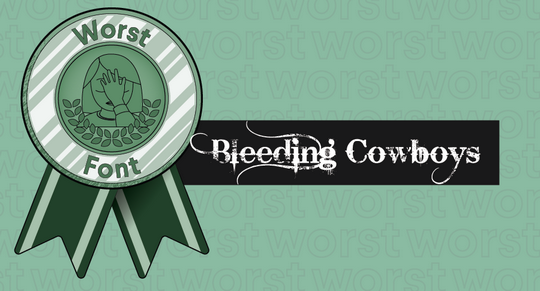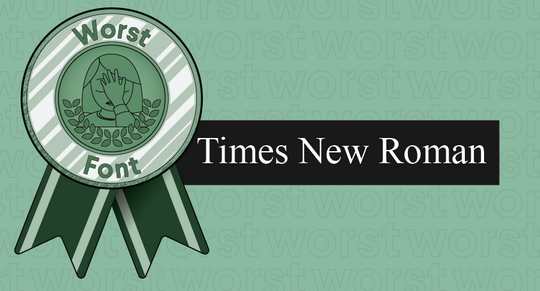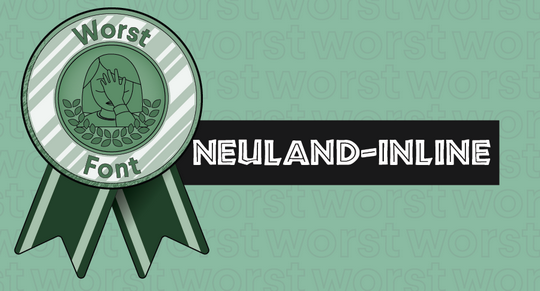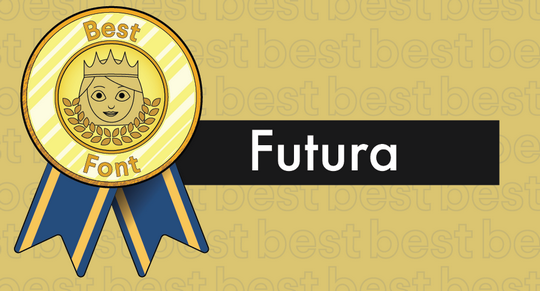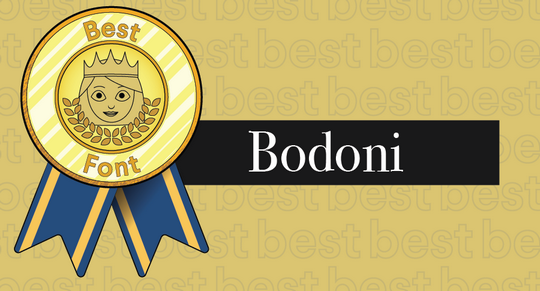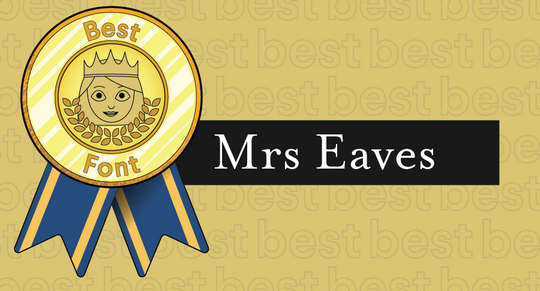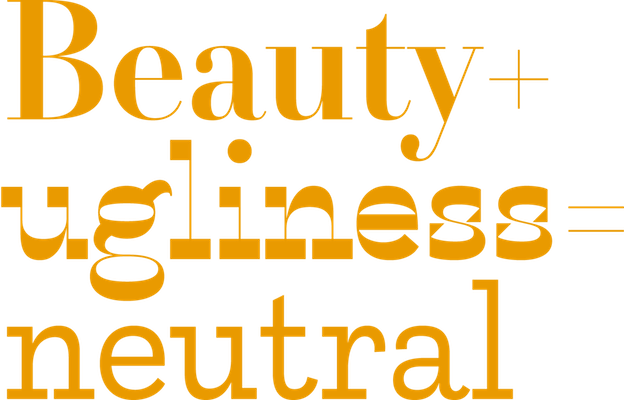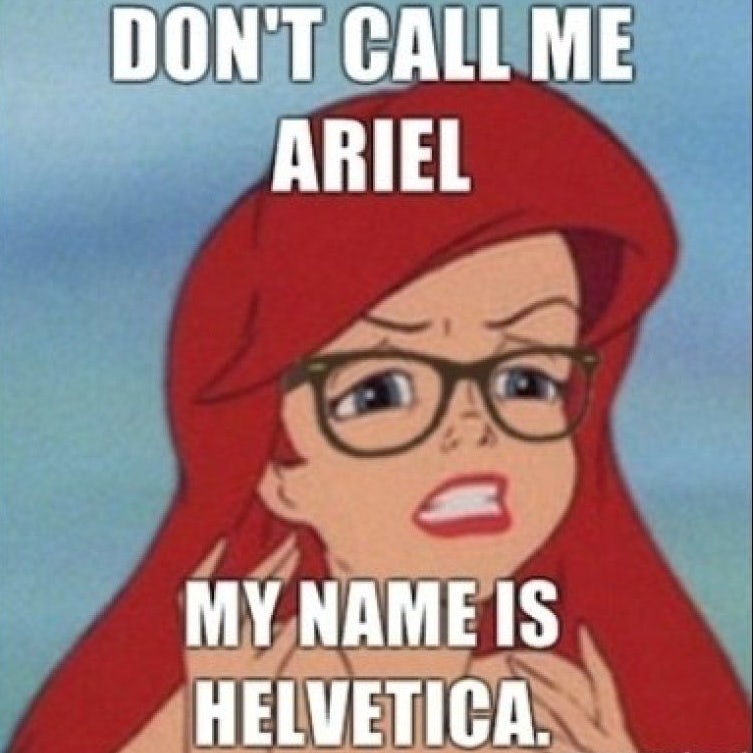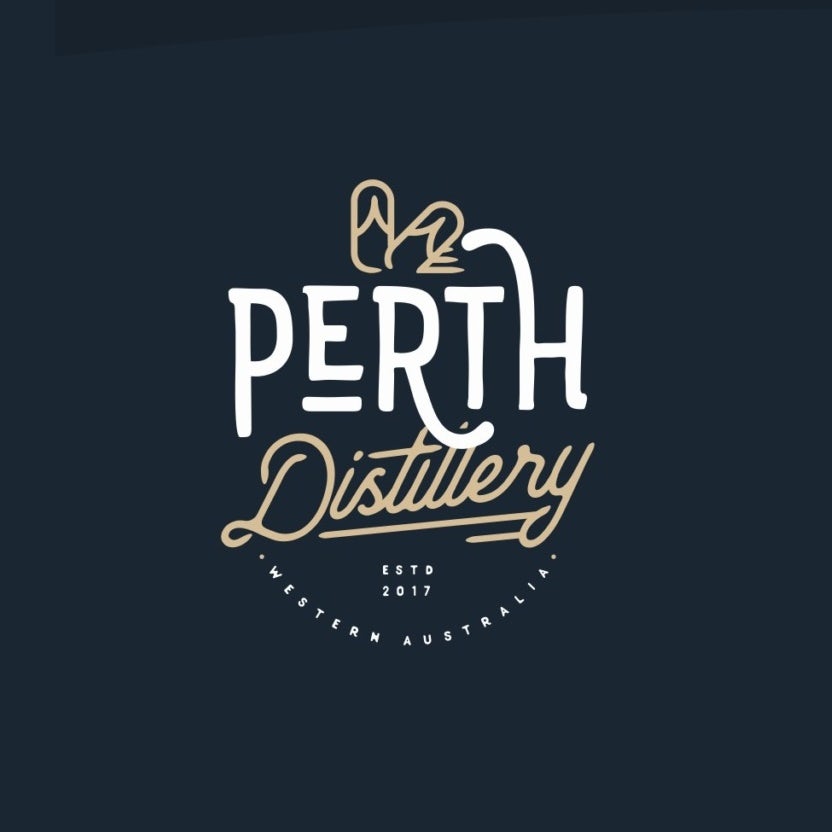
Шрифты – это наборы графических символов, используемых для представления письменного текста. Они включают в себя все символы алфавита, цифры, знаки препинания, специальные символы и другие графические элементы, которые позволяют создавать текстовую информацию в печатной или цифровой форме.
Шрифты используются в различных сферах, включая печатное издательство, веб-дизайн, графический дизайн, рекламу, упаковку, мобильные приложения и многое другое. Они играют важную роль в создании визуального образа текста и могут повлиять на восприятие контента аудиторией.
К счастью, в наши дни вы больше не ограничены шрифтами, предварительно загруженными в Microsoft Word. Тысячи хороших шрифтов доступны для скачивания в Интернете, а мир талантливых дизайнеров создает уникальные шрифты, такие же, как бренды, которые их используют. Не каждый шрифт хороший. На самом деле, есть тонна плохих шрифтов, скучных, неразборчивых и просто безобразных. Это не только наше мнение: есть научные причины, по которым некоторые шрифты выглядят красиво, а другие заставляют нас съеживаться.
Чтобы помочь вам найти идеальный шрифт для вашего проекта, мы рассмотрим лучшие и худшие шрифты, а также то, что делает их эффективными (или нет).
Некоторые из лучших шрифтов.
Что делает хороший шрифт?
Даже если они могут сильно отличаться друг от друга, у лучших шрифтов много общего. Это включает:
• Даже кернинг.
• Консистенция.
• Баланс.
• Разборчивость.
Кернинг.
Кернинг – это пространство между двумя символами. Слишком мало места, и шрифт не читается, потому что буквы смешиваются вместе. Слишком много места, и трудно сказать, предназначено ли это место для разделения букв или слов. Неравномерное количество места от буквы к букве? Это выглядит просто неловко и безобразно.
Futura и Helvetica – два примера шрифтов, которые очень легко читаются благодаря их равномерному кернингу – независимо от того, являются ли буквы жирными или тонкими, их расположение дает читателю ощущение чистого пробела.
Иллюстрированная награда за лучшие шрифты в сочетании с гарнитурой Futura
Futura – это чистый шрифт с равномерным кернингом
Консистенция.
Согласованность означает, что все буквы, цифры и любые другие используемые символы сохраняют одинаковый внешний вид. Если буква «A» шрифта имеет засечки, мы ожидаем, что у буквы B тоже будут засечки, и так далее.
Точно так же, если шрифт имеет толстые буквы с мягкими закругленными углами, но этот стиль не распространяется на его цифры или знаки препинания, шрифт кажется непоследовательным и даже неполным.
Иллюстрированная награда за лучшие шрифты в сочетании с гарнитурой Mrs Eaves
Mrs Eaves имеет равномерное распределение твердых краев по закругленным углам
Сбалансированные шрифты.
Сбалансированное сочетание толстого и тонкого, тяжелого и легкого, является важной составляющей хорошего шрифта.
Didot – превосходный шрифт, который использует драматические различия между толстыми и тонкими штрихами, при этом сохраняя равновесие. Bodoni – другой известный пример хорошо сбалансированного шрифта с его сильными, твердыми вертикальными штрихами и более легкими арками и изгибами. Его засечки добавляют немного стильного стиля, который также напоминает противовесы, держащие буквы в вертикальном положении.
Иллюстрированная награда за лучшие шрифты в сочетании с гарнитурой Bodoni
Bodoni имеет равномерное распределение веса, как классный шрифт
Разборчивые шрифты.
И, наконец, шрифт должен быть разборчивым. Шрифт, который вы не можете прочитать, похож на изображение, которое настолько занято, что вы не можете сказать, каким оно должно быть. Проверьте, является ли шрифт разборчивым, написав в нем различные слова, убедившись, что вы используете каждую букву и несколько разных буквенных комбинаций. Увеличьте его, затем уменьшите, чтобы увидеть, есть ли такой размер, при котором его становится трудно читать. Если вам нужен такой маленький текст, выберите шрифт с таким размером.
Иллюстрированная награда за лучшие шрифты в сочетании с гарнитурой Garamond
Garamond является классическим шрифтом, потому что он элегантен и разборчив в разных размерах.
Шрифты, которые выдержали испытание временем, как и Garamond, остаются популярными среди дизайнеров, потому что они разборчивы в различных размерах, цветах и ​​композициях. Sans Serifs особенно хороши для поддержания разборчивости независимо от контекста: отсюда и стойкость таких шрифтов, как Helvetica .
Некоторые из худших шрифтов.
Что делает шрифт плохим?
Есть много способов, которыми шрифт может быть плохим. Многие популярные шрифты были чрезмерно истощены. Шрифты, которые не сочетаются с нашим внутренним пониманием баланса, также выглядят ужасно. Еще больше шрифтов не работает, потому что их слишком много, чтобы их можно было прочитать, в то время как у других есть противоположная проблема: в них нет ничего уникального, поэтому они не выделяются. А еще есть шрифты, которые пытаются выглядеть экзотично, но при этом чувствовать себя так же аутентично, как и меню Taco Bell. Давайте разберемся, как худшие шрифты выглядят подробно.
Чрезмерно используемые шрифты.
Некоторые шрифты настолько перегружены, что стали универсальными. Некоторые известные примеры включаютCopperplate Gothic, Brush Script and Souvenir . Brush Script была чрезвычайно популярна с 1940-х по 1960-е годы до такой степени, что сегодня она все еще ощущается устаревшей и чрезмерно используемой. Точно так же «Сувенир» постоянно закрепляется в наших умах как «шрифт 70-х годов».
Иллюстрированная награда за худшие шрифты в сочетании с гарнитурой Trajan Pro
Trajan Pro использовался на многих постерах фильмов и обложках книг, что он потерял свою привлекательность.
Другие часто используемые ретро-шрифты, от которых вам следует держаться подальше? FF Blur and Trajan Pro. Это не значит, что они плохие шрифты как таковые. Они были сделаны так много раз, что теряют всякую привлекательность.
Несбалансированные шрифты.
Когда шрифт сбалансирован, мы читаем его как эстетически приятный.
красивые и некрасивые варианты шрифта шрифта Karloff желтого цвета
Когда мы видим дисбаланс, мы видим уродство, и когда шрифт полностью нейтрален, он читается как где-то посередине. через Питера Билака
Все это означает, что вес шрифта – расположение его более толстых линий – распределяется таким образом, что он не опрокинулся бы, если бы это был материальный объект.
Возьмите три варианта изображенного здесь Карлоффа: светильник типографии шрифта Питера Билака, разработанный для проверки его гипотезы о том, что распределение веса шрифта определяет, будет ли он уродливым или красивым. Худшие шрифты несбалансированы, что делает их уродливыми.
Нечитаемые шрифты.
Некоторые из худших шрифтов, такие как Jokerman , почти не нравятся , потому что они несут тонну бесполезного смысла, который отвлекает зрителей от текста, который они пытаются прочитать.
Другой известный непопулярный, уродливый шрифт, Bleeding Cowboys, не нравится дизайнерам из-за того, насколько он занят и непредсказуем. Случайное угасание букв? Откуда взялась эта линия и куда она пойдет?
Иллюстрированная награда за худшие шрифты в сочетании с гарнитурой Bleeding Cowboys
Ковбои кровоточат, как и наши глаза.
Скучные шрифты.
И еще есть шрифты, которые просто скучны, что делает их плохим выбором шрифта. В этих шрифтах нет ничего удивительного, потому что в них нет ничего выдающегося, точка.
Arial – один из примеров шрифта, который мы все видели миллион раз раньше. Он выполняет свою работу, но это все. Это ничего не добавляет к дизайну, оно не передает бренд осмысленно.
Хотя бывают случаи, когда неуместный шрифт – это именно то, что вам нужно, существует множество хороших шрифтов, которые могут придать индивидуальность при переходе на задний план (см. Ниже раздел «Лучшие шрифты»). Обычный шрифт, такой как Times New Roman , настолько ничем не примечательн, что на самом деле может отвлечь внимание.
Иллюстрированная награда за худшие шрифты в сочетании с гарнитурой Times New Roman
Times New Roman распространена не только потому, что она отходит на задний план – она ​​вообще лишена индивидуальности
Fauxotic ™ шрифты.
Некоторые из худших шрифтов восполняют отсутствие индивидуальности с подражанием. Comic Sans , например, не в состоянии собрать супергероя из комиксов, написанных от руки. И если вы не пишете сценарий фильма, Courier  никого не обманет тем, что ваш опус был написан на старинной пишущей машинке.
Некоторые шрифты выглядят экзотично, имитируя элементы дизайна, связанные с конкретными культурами. Papyrus и Neuland-Inline являются одними из самых известных преступников. А  Bonzai’s letters имитируют мазки кисти, используемые в китайской каллиграфии, ручной характер которых теряется на статическом шрифте. Основная проблема с этими шрифтами заключается в том, что они выглядят одинаково и в лучшем случае выглядят дешевыми, а в худшем – культурно нечувствительными.
Иллюстрированная награда за худшие шрифты в сочетании с гарнитурой Neuland-Inline
Шрифты, которые соответствуют другим культурам, чувствуют себя отвратительными и нечувствительными в 21-м веке
Выбор лучшего шрифта для вашего дизайна.
Хотя плохие шрифты – это повсеместно плохой выбор, хороший шрифт автоматически не является хорошим выбором для вашего проекта. Правильный шрифт для вашего дизайн-проекта должен состоять из двух вещей:
• Хорошо продуманный и эстетичный
• Подходит для вашего бренда
круглый логотип с геометрическими линиями, показывающими ромбовидную форму рядом с геометрическим шрифтом
Этот шрифт продолжает геометрический облик, созданный логотипом этой компании, создавая современную, ориентированную на точность индивидуальность бренда.
В дизайне Arthean для Planet Diamonds мы видим прекрасный пример шрифта, который идеально подходит для его бренда . Planet Diamonds создает выращенные в лаборатории бриллианты для своей ювелирной линии, предоставляя экологичным потребителям еще один вариант на рынке. Благодаря угловатому минималистичному шрифту, который соответствует геометрическому логотипу компании, брендинг отражает ориентацию Planet Diamonds на использование технологии для создания безупречных бриллиантов без негативного воздействия на окружающую среду.
Логотип Wordmark с тремя различными стилями шрифтов
Различные шрифты и стили надписей передают разное настроение для бренда, который они представляют.
Когда вы пытаетесь выбрать правильный шрифт для вашего проекта, подумайте, что вы хотите, чтобы проект передал.
Подумайте, как персона вашего бренда переводится на различные типы ассоциаций шрифтов .
Как правило, шрифты с засечками, такие как Mrs Eaves и Baskerville, создают утонченность и неподвластную времени роскошь, поэтому они популярны среди более высококлассных брендов. С другой стороны, более простые, неформальные бренды, как правило, используют шрифты без засечек, такие как Akzidenz-Grotesk . Если личность вашего бренда требует рукописного стиля, вам лучше получить нестандартные надписи, а не выбирать унифицированный шрифт, имитирующий нарисованный вручную вид (см. Fauxoitc выше).
Мем Русалочки как хипстера "Не называй меня Ариэль, меня зовут Гельветика"
Impact – это шрифт мемов, а Arial – это имя, с которым вы не хотите ассоциировать себя
Также подумайте об ассоциациях людей с определенными шрифтами. Любите их или ненавидите, мемы неразрывно связаны с Impact, так что этого стоит избегать, если только вы не стремитесь к этому чувству мема.
Итак, взгляните на каждый шрифт, который вы рассматриваете для своего дизайн-проекта, и спросите себя:
• Могу ли я прочитать это легко?
• Это соответствует моему бренду?
Если вы ответите «да» на оба вопроса, вы нашли свой шрифт! Если нет, продолжайте пробовать другие шрифты на своем месте, пока не найдете тот, который лучше всего подходит для вашего бренда.
Лучший шрифт  стоит усилий.